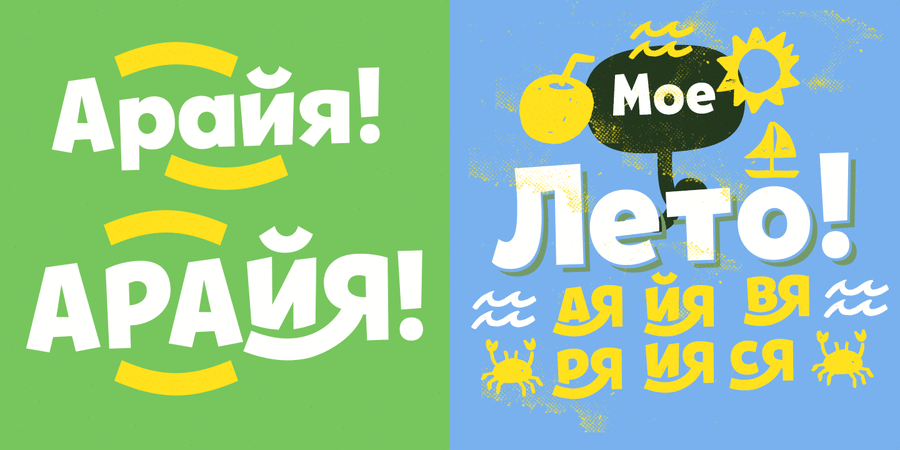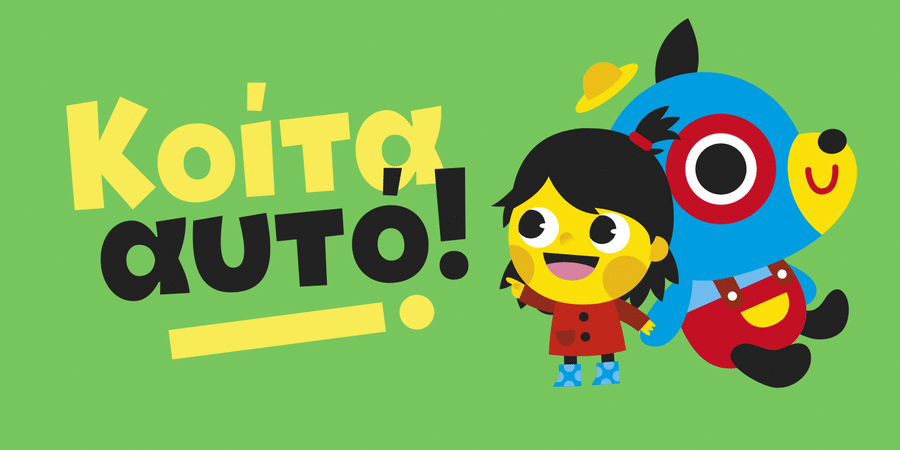
Шрифт Tobi Greek Cyrillic створений на базі шрифту Tobi зі значними поліпшеннями у вигляді альтернативних гліфів, великого набору лігатур, а також грецьких та кириличних символів. Це дуже радісний шрифт, що підходить для заголовків і логотипів дитячої продукції, книжок чи коміксів. Tobi Greek Cyrillic створений з великою любов'ю!
Шрифт розробив Родріго Арая Салас та Андрій Кудрявцев у 2018 році.
стінгазета, журнал, комікс, пакування, листівка, анімація, мультфільм, вивіска, обкладинка, плакат, реклама, етикетка, афіша, меню, відео, стікер, наліпка, привітання Адаптованість гарнітури до носіїв:
Асоціації з сімейством шрифтів Tobi Greek CyrillicОсобистість і характер гарнітури:
виразний, потішний, іронічний, здоровий, бадьорий, характерний, гулящий, дозвільний, пещений, круглий, щедрий, гладенький, студентськиий, тусовочний, прикольний, динамічний, живий, доброзичливий, привітний, неформальний, молодіжний, яскравий, веселий, задерикуватий, смішний, добродушний, добрий, радісний, грайливий, пустотливий, рухливий, оригінальний, свіжий, стиглий, смачний, помітний, дитячий, карикатурний, мультяшний, новорічний, дотепний, літній, щасливий, святковий, творчий, важкий, тонкий, наївний, гострий, блискучий, милий, домашній, М'який, затишний, усміхнений, апетитний, солодкий, неохайний, крафтовий, ручний, рукотворний, артізанальний, недбалий, вернакулярний, нервовий, емоційний, кольоровий, інфантильний, зелений, пластичний, примітивний
дача, хенд мейд, фаст фуд, крамниця, графіті, гурток, олівці, іграшка, пригоди, розваги, вечірка, торгівля, реклама, магазин, зоопарк, гра, кафе, дитяча книжка, канцтовари, школа, табір, гумор, анімація, сніданок, їжа, закуска, розфарбування, відпочинок, щоденник, цирк, мультфільм, Новий рік, дитсадок, дитячий ранок, селфі, канікули, зошит, піцца, базар, графіка, ілюстрація, ранок, свято, кіно, атракціон, прикраса, казино, десерт, солодощі, кондитерська, випічка, булочна, фарби, фарба, клоун, пончик, зоомагазин, тварини, торт, цукерки, згущене молоко, варення, подарунки, день народження, смузі, учень, школяр, школярка, дім, тусовка, фестиваль, ярмарок, Хюґе Гарнітура має ознаки стилів: